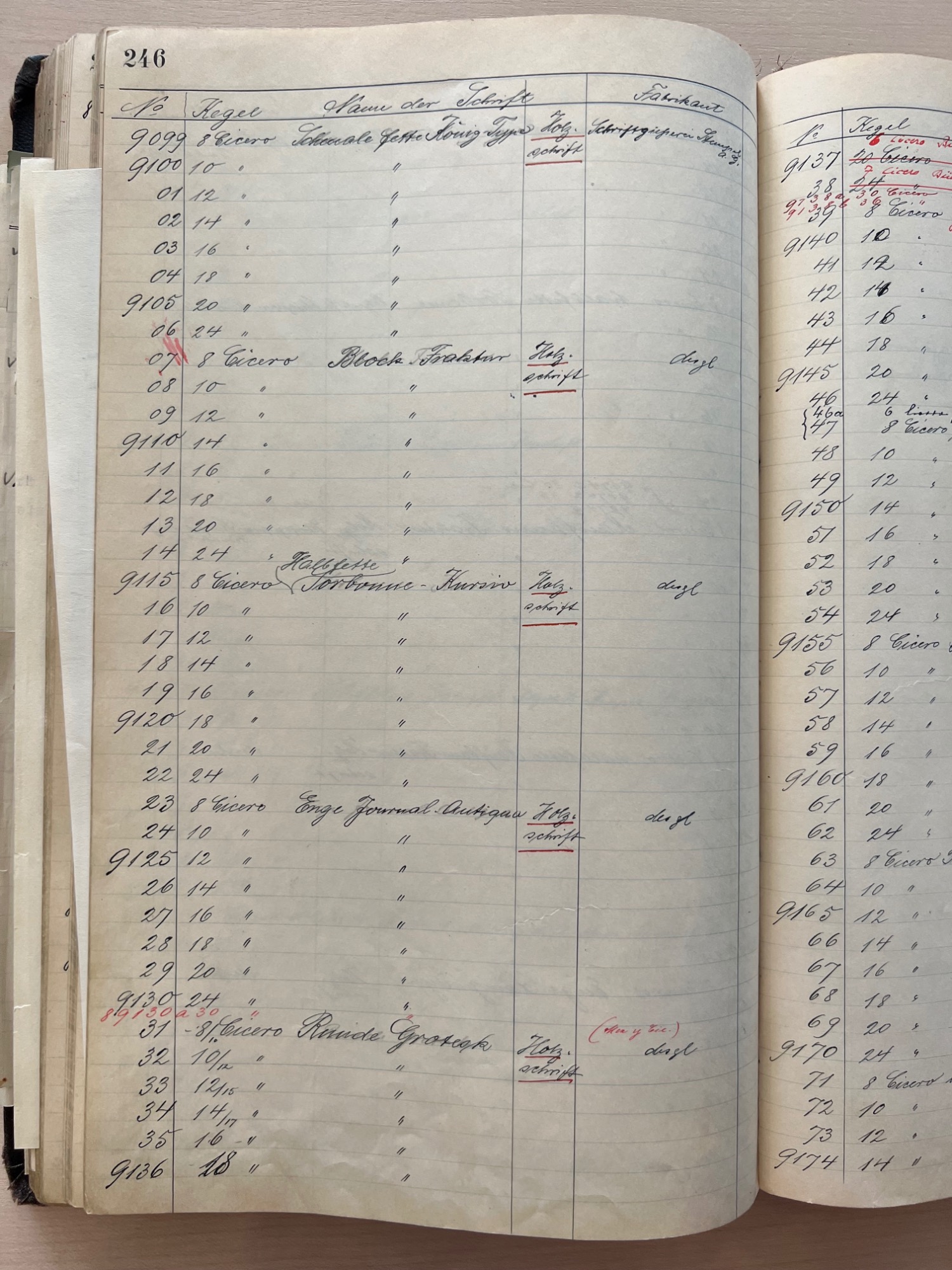
Schriftmuster Berthold Grotesk rund
ich bin auf der Suche nach einem Schriftmuster der Berthold Grotesk rund, das über das angehängte Muster hinausgeht. Dieses stammt von der Seite des "berlin.museum-digital.de" aus der Berthold Schriftprobe Nr. 310 - Holschriften.
Vielleicht kennt ja jemand eine andere Schriftprobe in der die Schrift ebenfalls enthalten ist.
Diese Runde Grotesk entstand nicht bei Berthold direkt.
Das Design ist Anfang 1886 bei der Schriftgießerei Ferd. Theinhardt erschienen (eine Firma, die wiederum nichts mit der Entstehung der Akzidenz- oder Royal-Grotesk zu tun hatte). Die erste Probe der Schrift erschien Januar 1886 als Beilage im Archiv für Buchdruckerkunst. Ein Scan der Beilage habe ich hier hochgeladen.
Einige wenige Infos zur Schrift stehen auch in meiner Datenbank von Groteskschriften, die im Laufe des 19. Jahrhunderts in deutschsprachigen Ländern verkauft worden waren. Bitte Beachten, dass ich dort Berthold leider nicht erwähne, weil Berthold erst 1908 mit der Übernahme der Schriftgießerei Ferd. Theinhardt die Schrift in ihrem Lieferprogramm aufgenommen hat.
Die Bleisatzgrade der Schrift dürfte in allen Berthold-Proben erscheinen, die ab 1909 bis in den 1920er-Jahren erschienen seien, wie etwa hier als Enge fette Grotesk.
Letztens habe ich beim Deutschen Technikmuseum in Berlin ein handschriftliches Registerbuch von Berthold, in dem die Herkunft ihren Schriften erwähnt wird, also für jeden einzelnen Schriftgrad (Titel: Berthold-Schriften, Signatur: SDTB/Hist. Archiv I.4.327 NL Möllenstädt). Auf Seite 246 der Liste steht es, dass die 8/10 Cicero, 10/12 Cicero, 12/15 Cicero, 14/17 Cicero sowie 16 Cicero und 18 Cicero Grade der Runden Grotesk – mit den Produktnummern [8]9131–[8]9136 – Holzschriften sind, die bei der »Schriftgießerei Stempel A. G.« fabriziert worden waren (siehe S. 246; ein Fotos ist hänge ich hier bei).
Das mit Stempel kommt bei richtig viele von deren Holzschriften vor. Ich vermute, dass Berthold die Holzschablone für ihre eigene Holzschriften-Herstellung bei der D. Stempel AG produzieren ließ. Zwischen den 1920er und Früh-1950er-Jahren gab es mehrer Partnerschaften zwischen Berthold und Stempel. Beide betrieben zusammen eine Schriftgießerei in Wien, z. B., und beide waren Teilbesitzern von denselben kleineren Schriftgießereien in In- sowie im Ausland.
Gibt es eventuell eine Jahreszahl zum Erscheinen der Holzlettern bei Berthold?
Das habe ich keine Indizien, leider. Ich vermute aber irgendwann Ende der 20er/Anfang der 1930er-Jahren. Auf jeden Fall nach dem Ersten und vor dem Zweiten Weltkrieg.